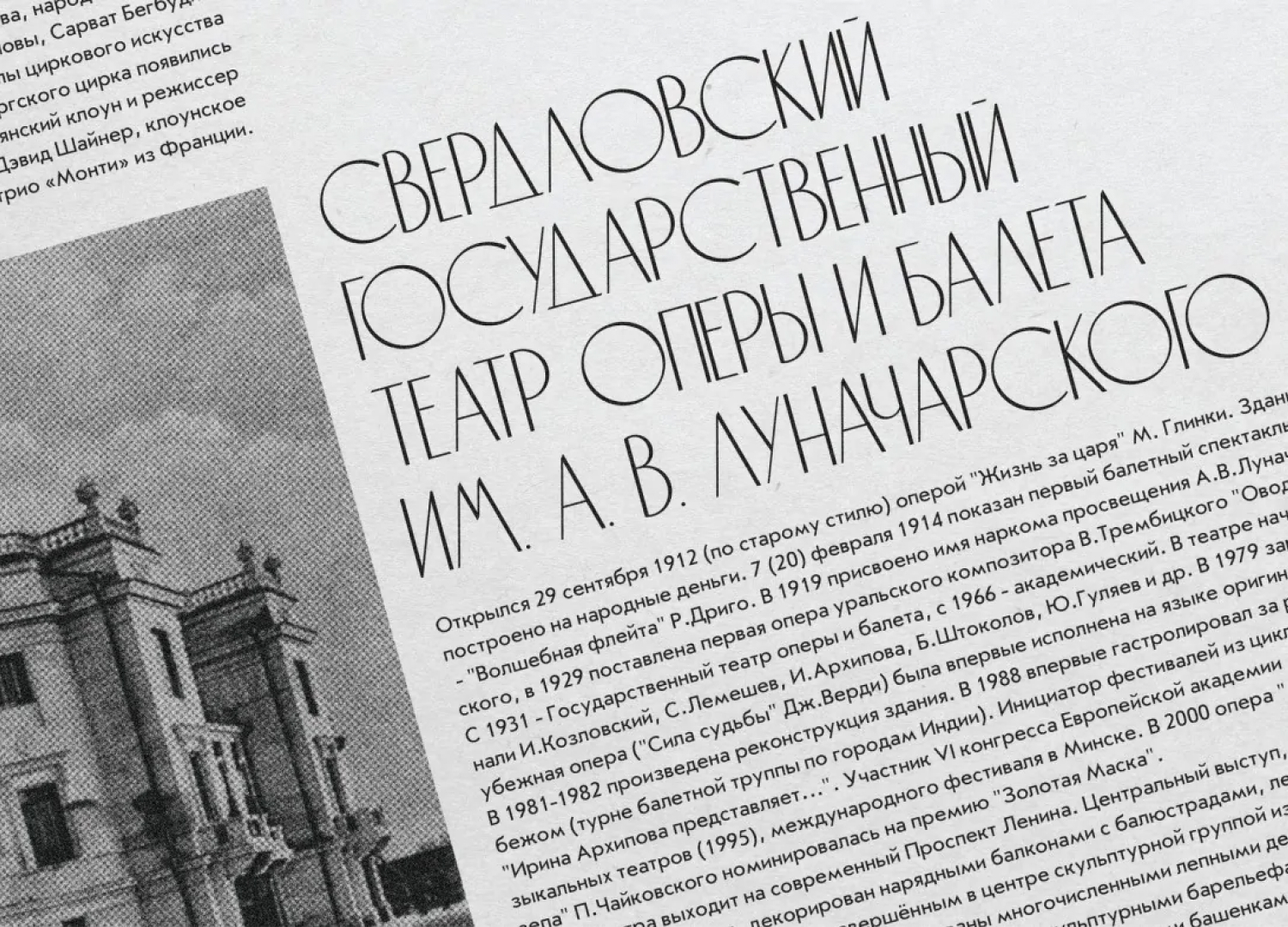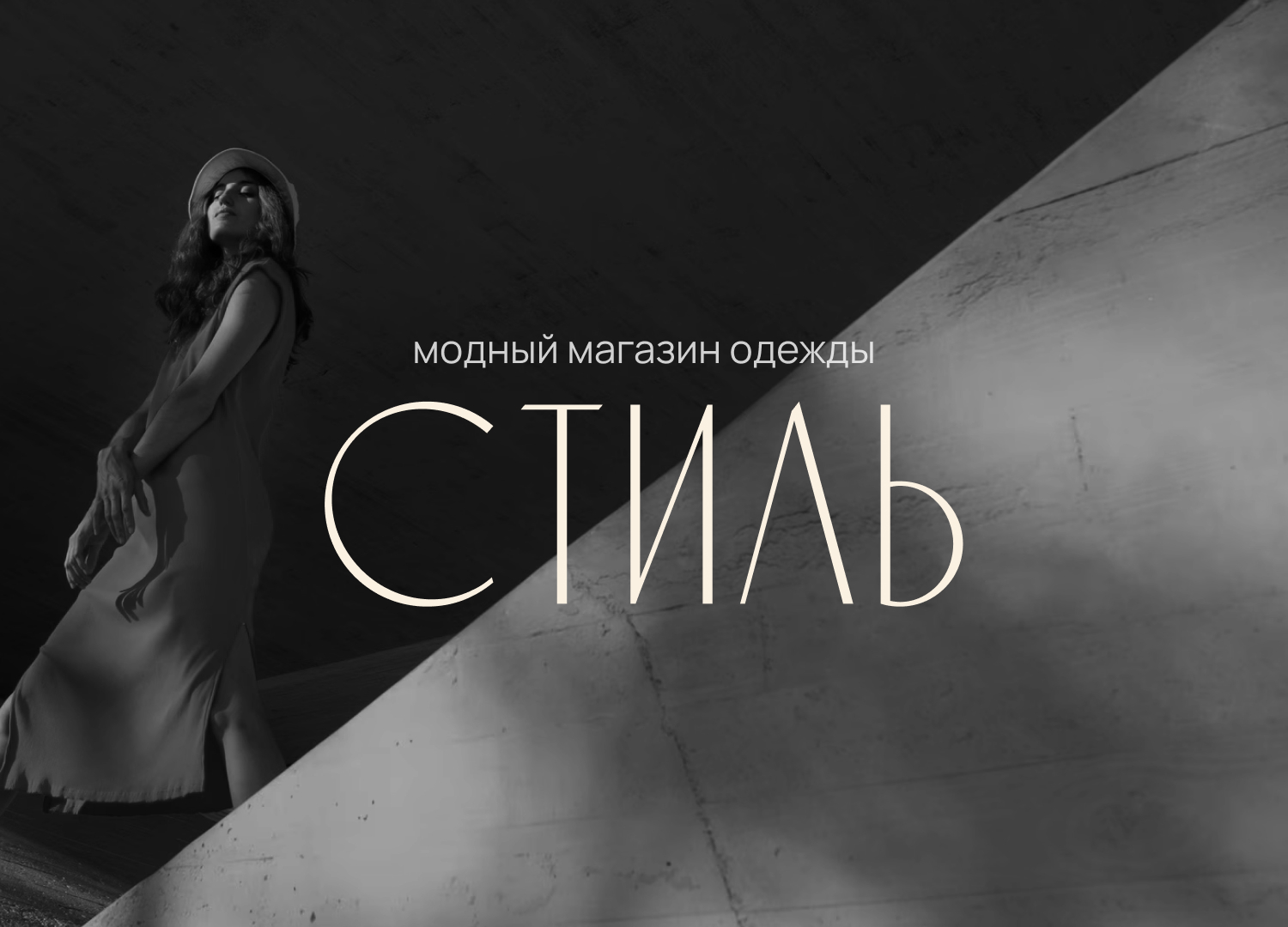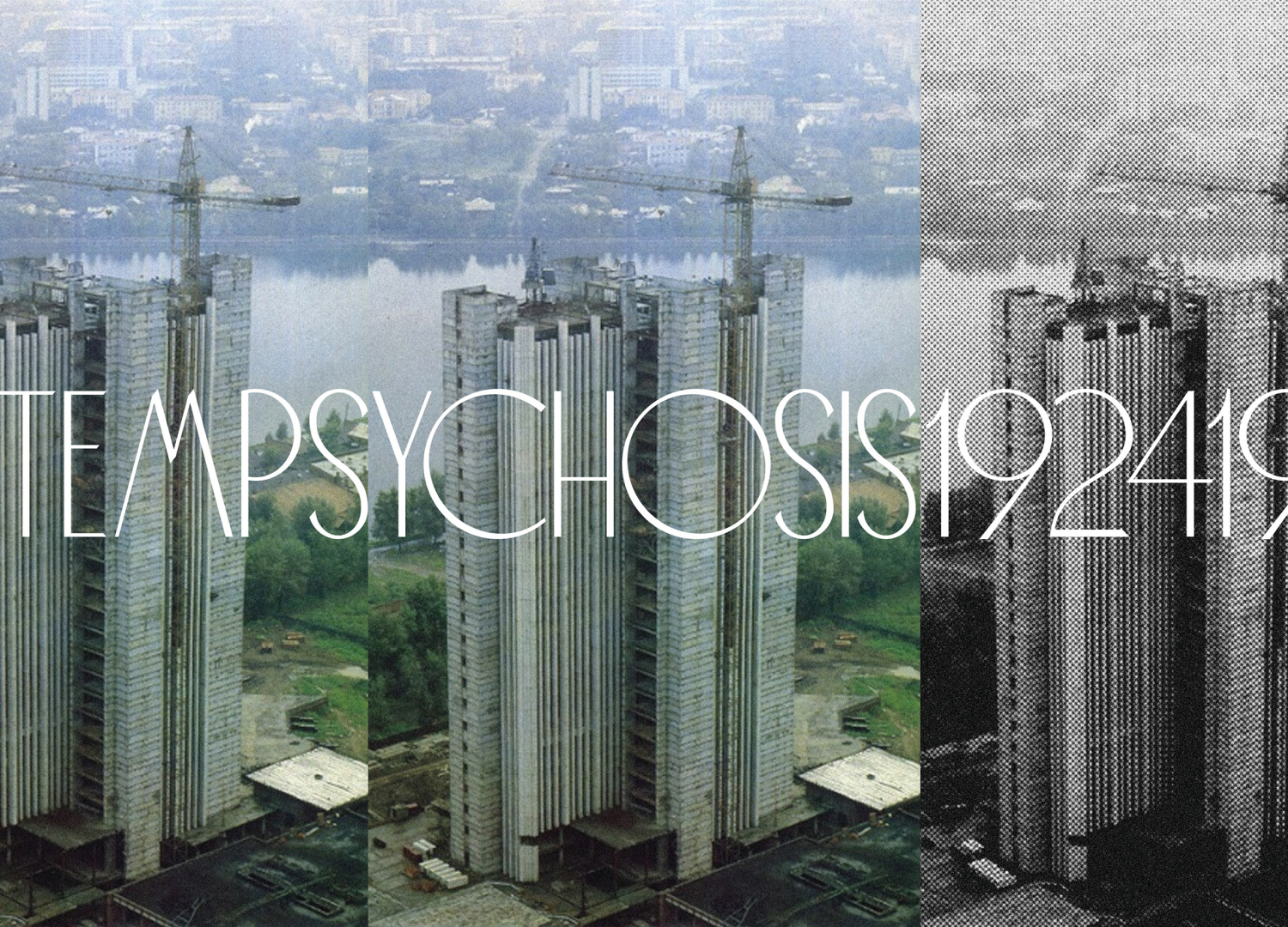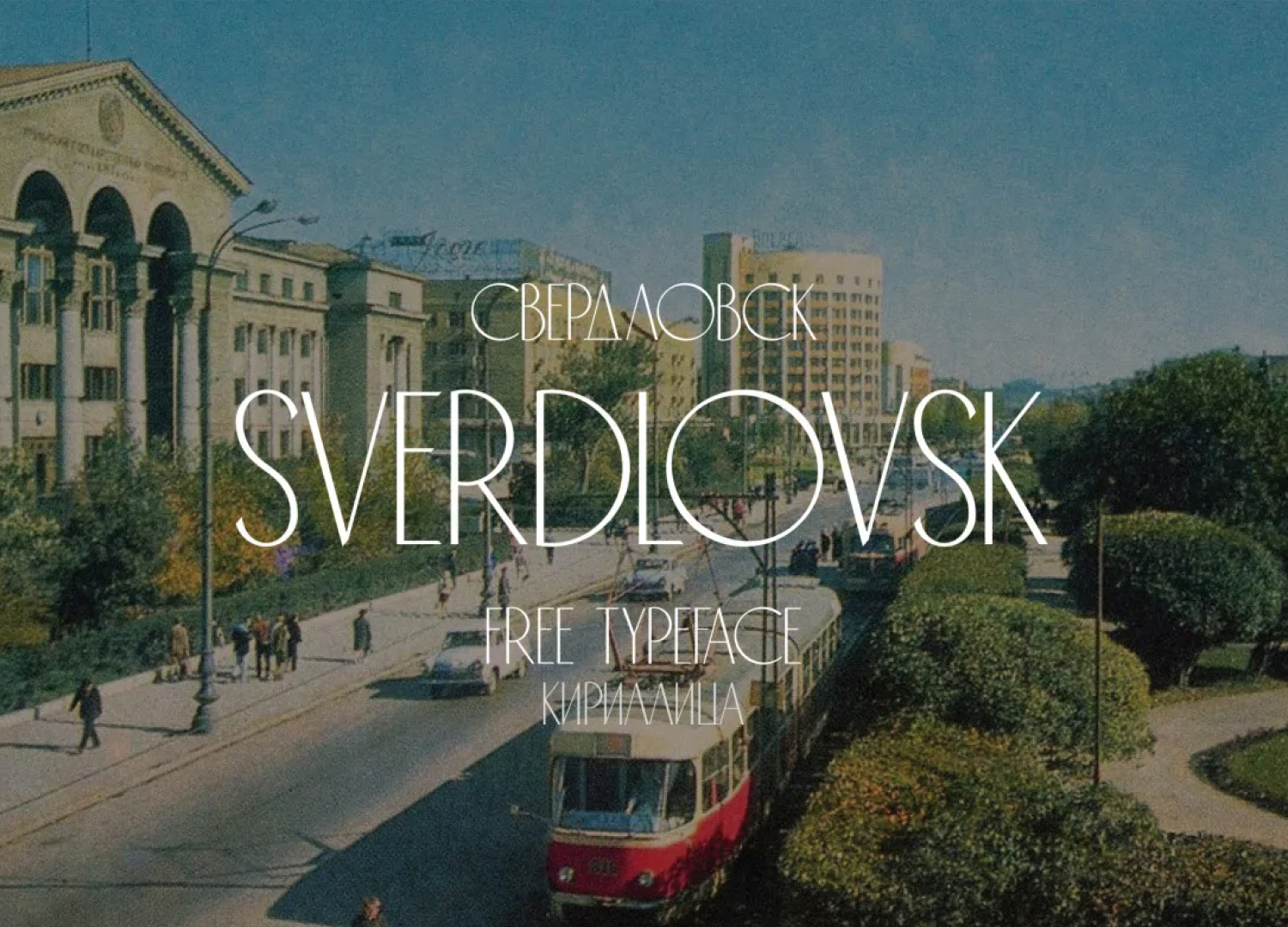
Шрифт Sverdlovsk
Старенький, но все же моднявый кириллическийшрифт. Презентацию частично сохранил от автора. Она в целом хороша. Почему то я был уверен, что публиковал его) Но не нашел в своем архиве.